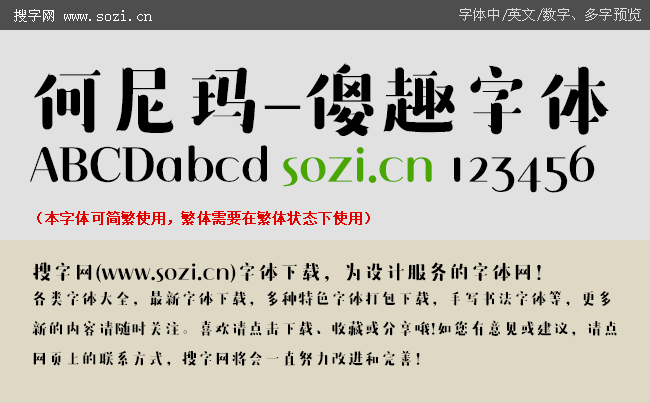
傻趣字體
搜字網(wǎng)給大家提供一款傻趣字體手機(jī)中文字體下載。這款手機(jī)字體是一款以粗宋體為原形的變形字體。字體筆畫(huà)及結(jié)構(gòu)進(jìn)行了較大變化,使之成為一款非常有趣的字體,特別適合喜歡手機(jī)字體個(gè)性一些的朋友在手機(jī)上安裝使用。